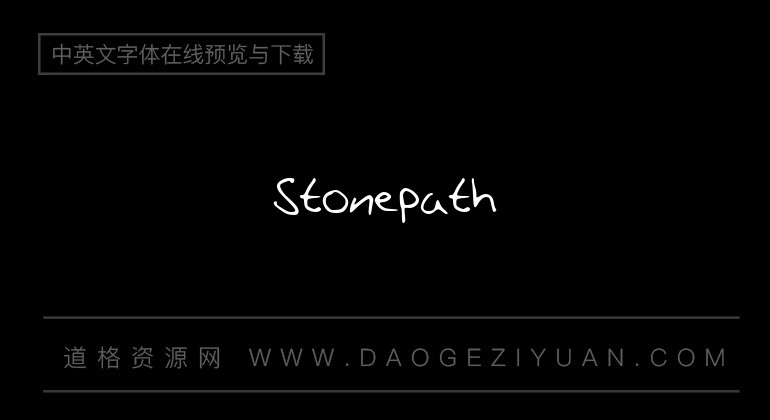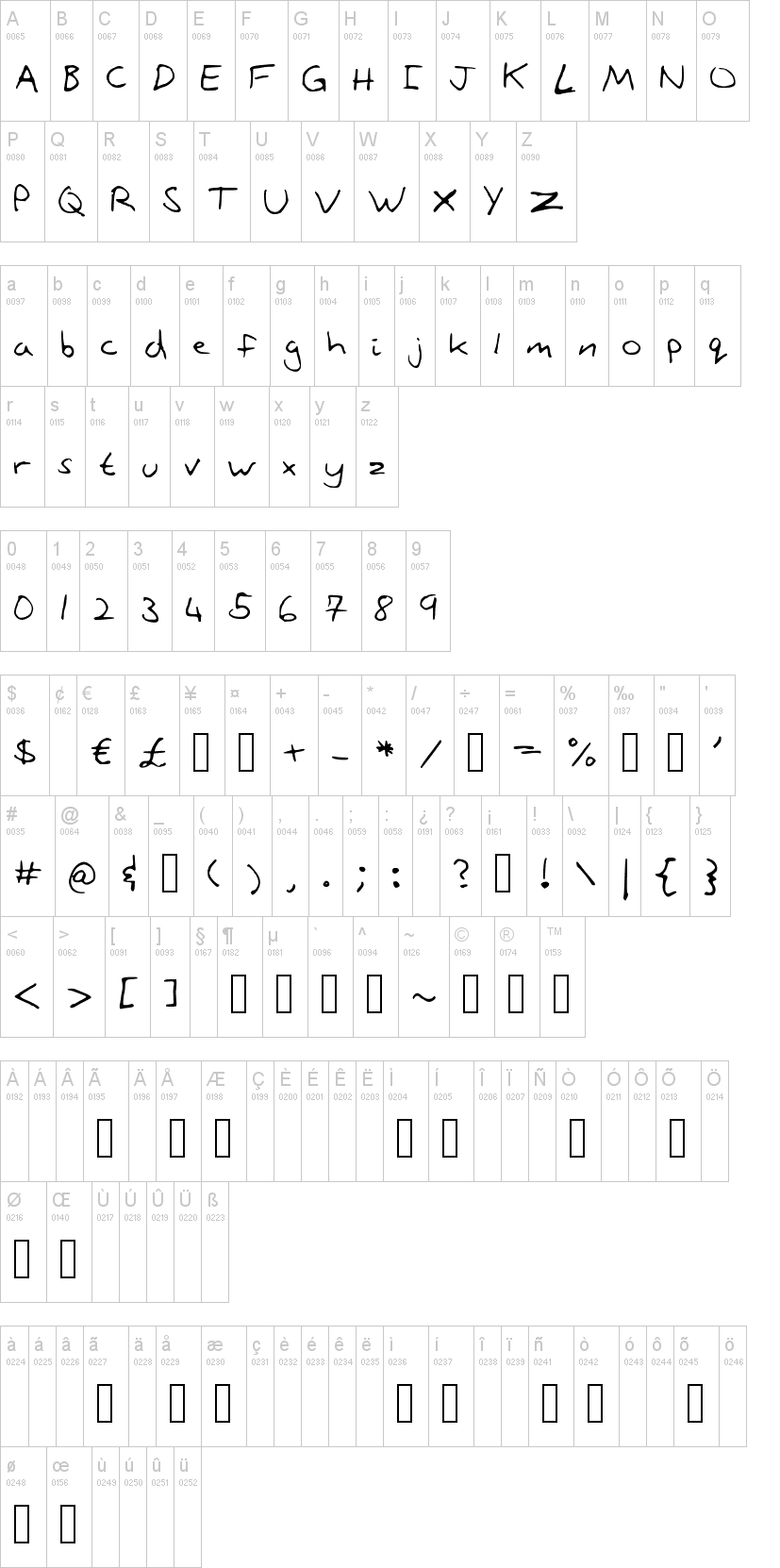
Stonepath
Stonepath 是一款由 Monotype 推出的抒情体字体,它拥有温柔、优雅的风格,特别适用于标题和短文本。Stonepath字体的字形细节更加精致,它的设计元素包括圆润的曲线、柔和的角度和大量的细节,让字体显得更加有质感。Stonepath 字体的特点是其强大的表现力,它可以轻松地融入不同的文本类型,从而为文本增添活力和色彩。
Stonepath是一款非常不错的手写艺术字体,具有很好的视觉感,适合于文化类的宣传设计、商业类品牌的广告和产品包装设计以及个性化文字排版等较多场景。